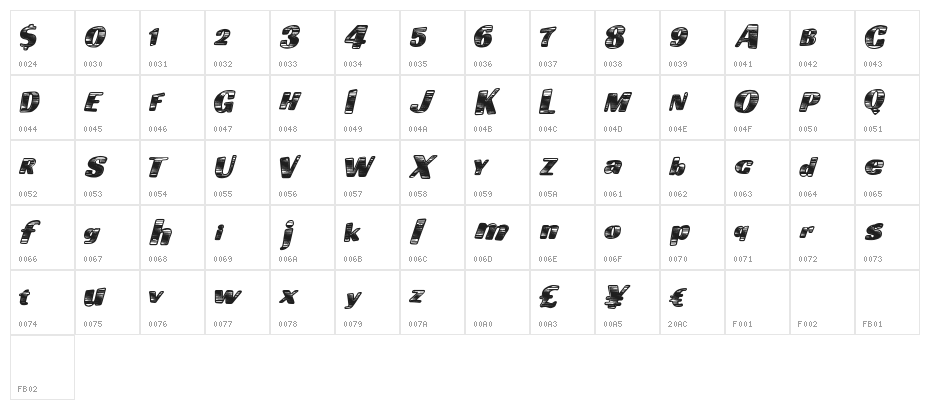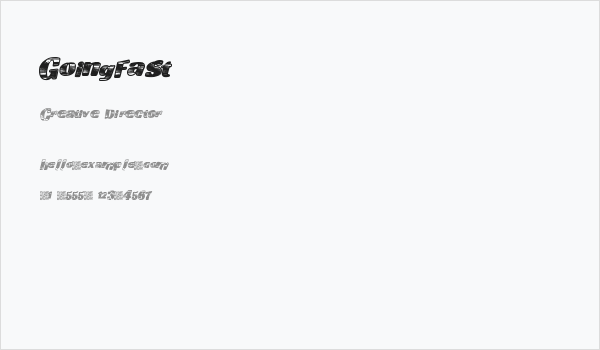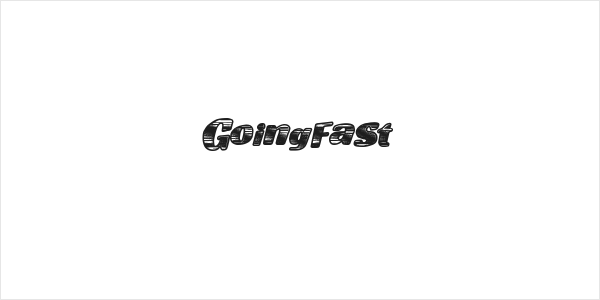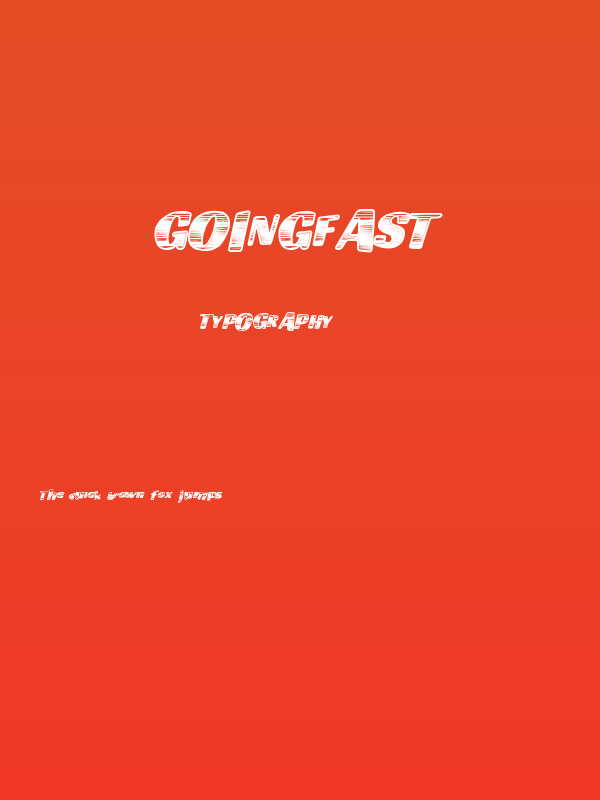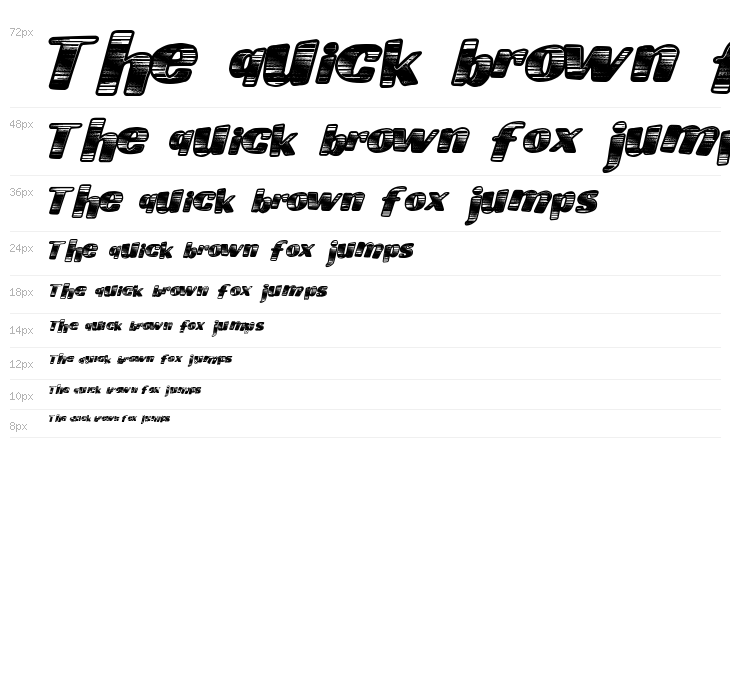
GoingFast Font
| Progetti proposti | Ideal for projects requiring a dynamic and eye-catching design, such as sports branding, posters, or event flyers. |